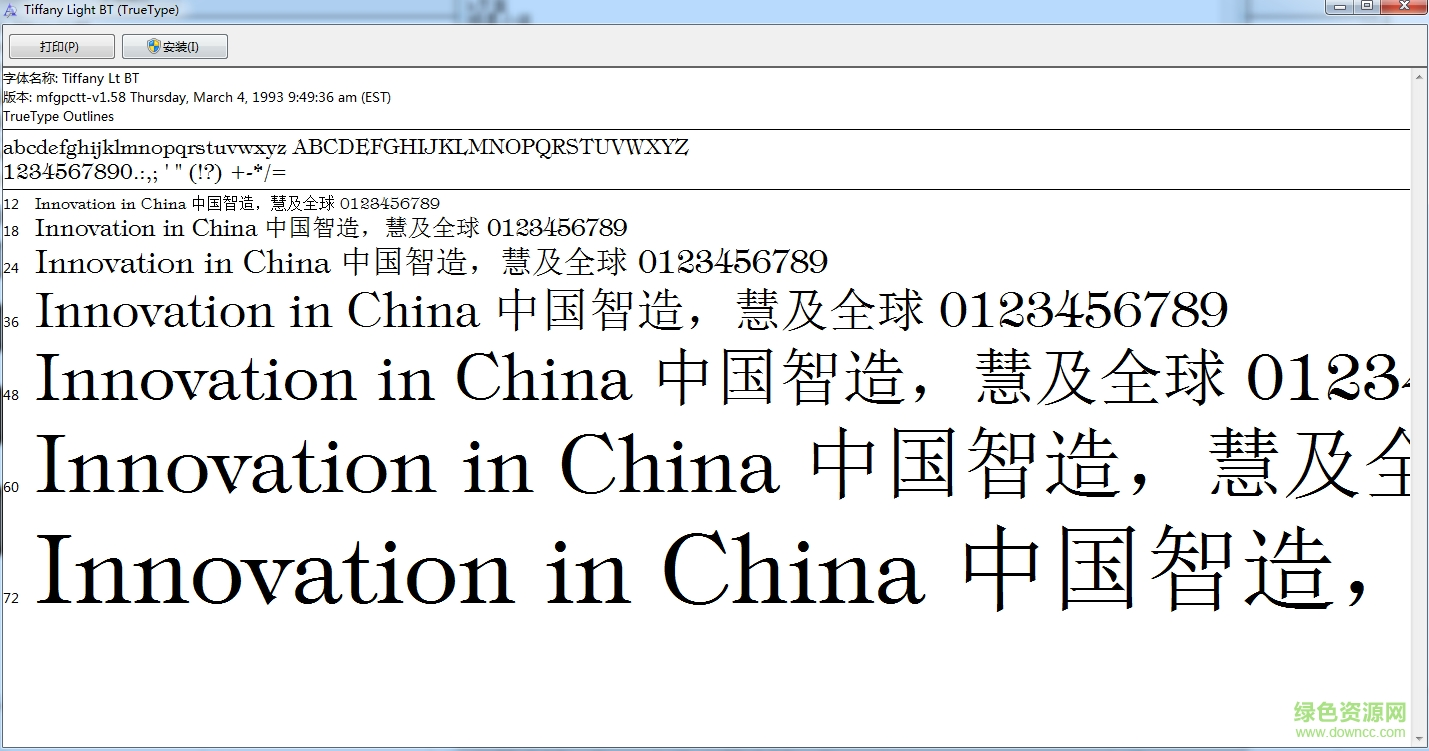
tiffany lt bt普通字體是一款常見的英文字體,精致細(xì)膩,具有文化氣質(zhì),小編為大家搜集了tiffany lt bt的普通體、斜體、細(xì)體、粗體等共5款字體,有需要者歡迎在綠色資源網(wǎng)下載收藏!
TRANSITIONAL AND MODERN (過渡型和時尚襯線字體組)
作為啟蒙思想的產(chǎn)物,Transitional字體和Modern字體產(chǎn)生于字體設(shè)計(jì)師們想試著讓字體比低調(diào)的老式字體更幾何感,更尖銳,更藝術(shù)感一些。Transitional字體標(biāo)志著在這一方向上適度的進(jìn)步,盡管它經(jīng)典的字體Baskerville看上去那么尖銳以至于人們堅(jiān)持說看著它有損視力。
它的優(yōu)點(diǎn)是:強(qiáng)勁有力,時髦,有活力;
它的缺點(diǎn)是:很難定位,太顯眼太巴洛克風(fēng)格以至于不夠經(jīng)典,太庸俗以至于不夠真正的時尚。
在創(chuàng)造Modern字體的過程中,字體設(shè)計(jì)師沉迷于對線條粗細(xì)的強(qiáng)烈對比的展示,這也是受到創(chuàng)造出兩個相似字體Bodoni和Didot的兩個設(shè)計(jì)師競爭的影響。
GEOMETRIC SANS (幾何型無襯線字體組)
事實(shí)上這里我合并了三種不同的組(Geometric, Realist和Grotesk),但是他們的共同點(diǎn)已經(jīng)足以讓我們把它們放在一起了。Geometric Sans-Serifs 是一類嚴(yán)格的基于幾何形體的字體。通常它的每一個字母粗細(xì)都一樣,并且遵循著簡單設(shè)計(jì)的原則。
它的優(yōu)點(diǎn)是:清晰,大方,時尚,很通用;
它的缺點(diǎn)是:冷酷,沒有感情色彩,乏味。
一個經(jīng)典的Geometric Sans就像一個設(shè)計(jì)的很漂亮的飛機(jī)場,它讓人印象深刻,現(xiàn)代感十足并且十分有用,但是如果讓我們考慮一下是否愿意住在這樣的地方,我們不得不再三考慮考慮。